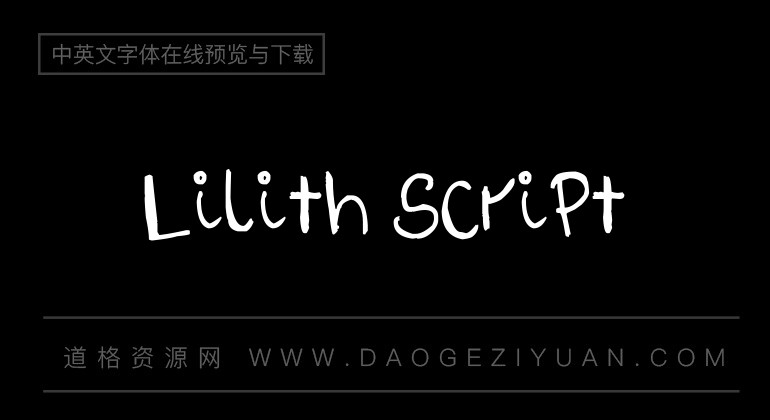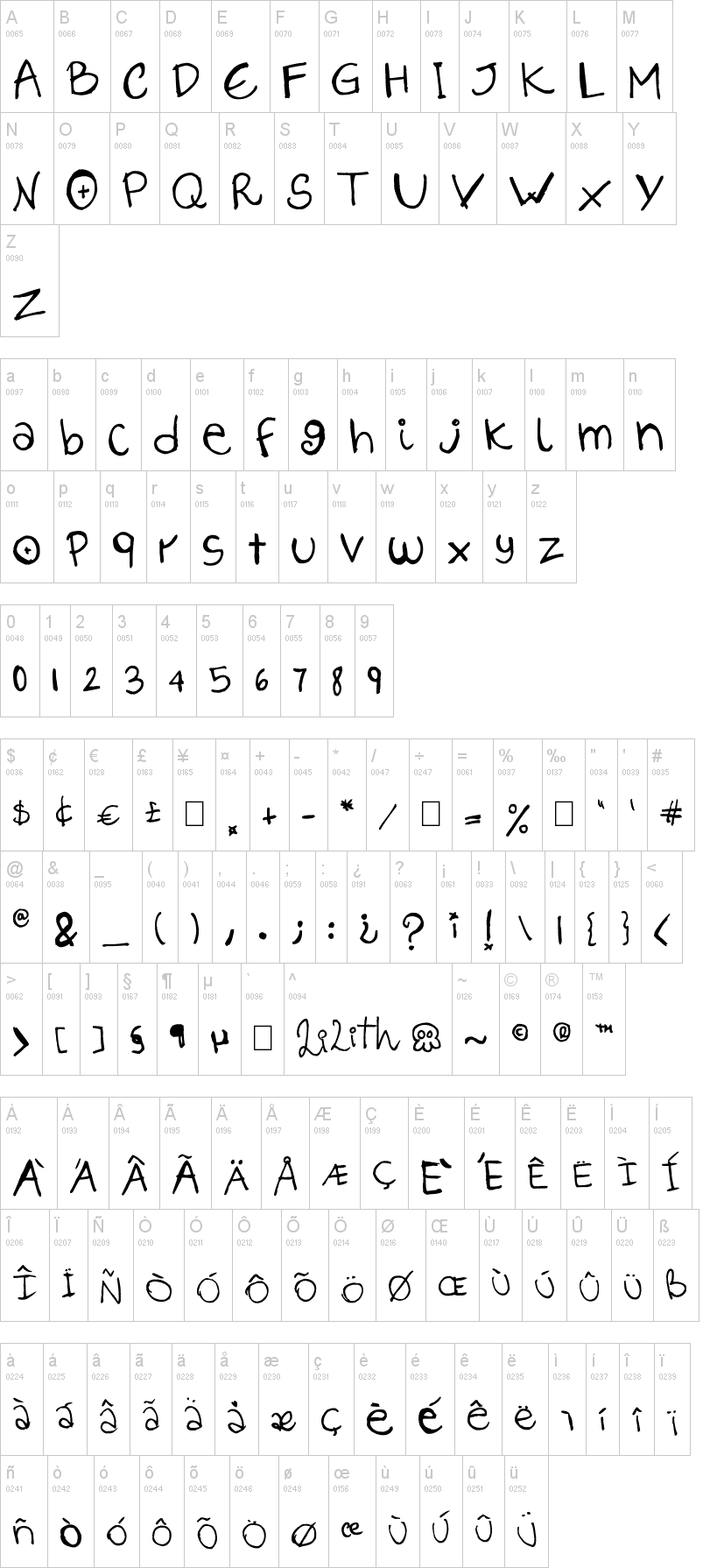
Lilith Script
Lilith Script 字体是一种手写风格的字体,具有流畅的曲线和自然的笔画。它源自于真实手写字体,是一种非常适合用于设计、广告、艺术和手写风格文本的字体。 Lilith Script 字体由60余个字符和标点符号组成,包括大小写字母、数字、标点符号和特殊符号,使它非常适合用于设计各种类型的文本,例如:海报、传单、宣传册、包装、品牌标识和其他创意设计项目。 Lilith Script 字体的特点是具有自然、艺术化和优美的线条,其笔画在字母之间和字母内部自然流畅,使得它非常适合用于需要手写风格文本的创意作品。 总的来说,Lilith Script 字体是一种非常漂亮且易于阅读的手写风格字体,适用于各种创意设计项目。
Lilith Script是一款非常不错的手写艺术字体,具有很好的视觉感,适合于文化类的宣传设计、商业类品牌的广告和产品包装设计以及个性化文字排版等较多场景。
Lilith Script字符映射图